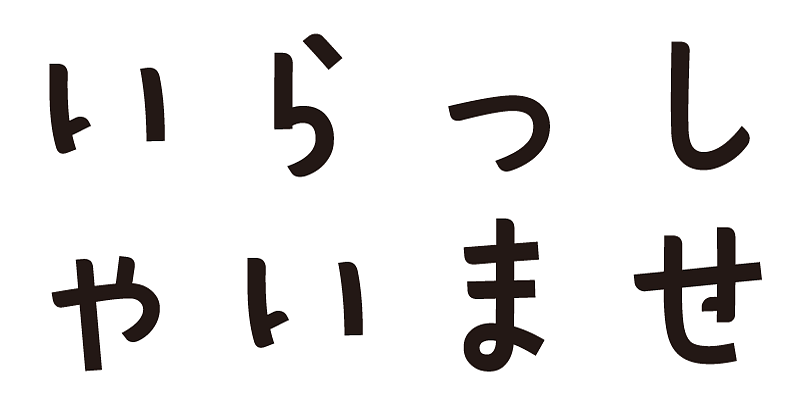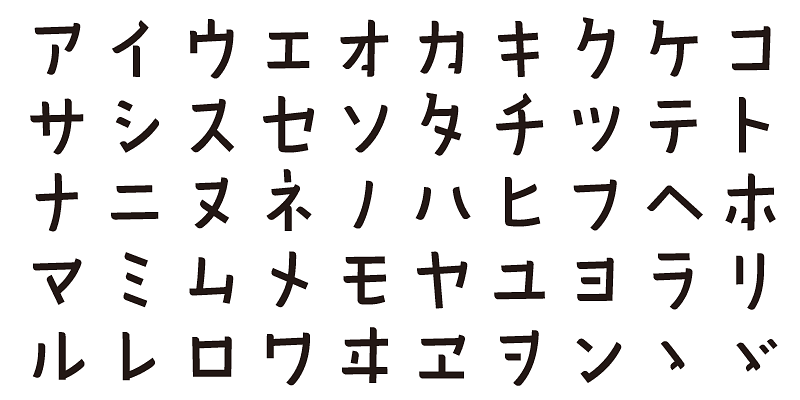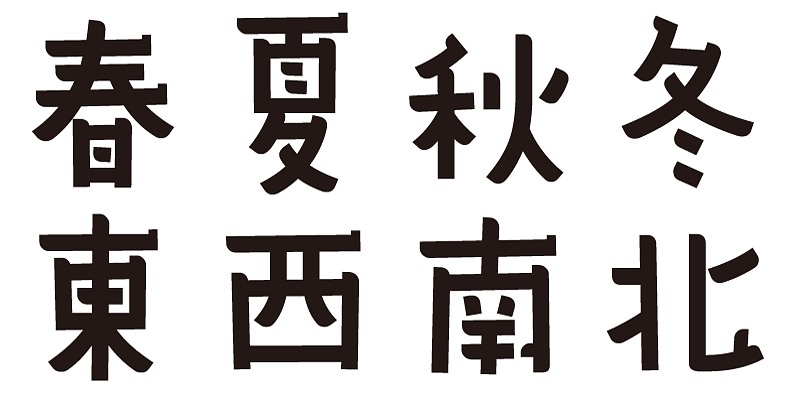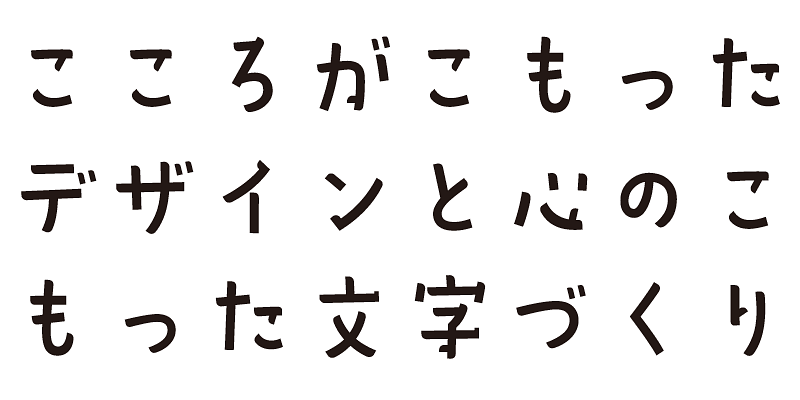
Diese Schrift wirkt sympathisch und frei, wie von Hand gezeichnet.
Jede Schrift dieser Familie enthält neben 1.000 Kanji-Zeichen auch Hiragana- und Katakana-, alphanumerische und Interpunktionszeichen.
Wir entwerfen Schriften in der Hoffnung, dass sie den ausgedrückten Worten eine tiefere Bedeutung verleihen. Wir möchten, dass sich der Benutzer bei der Verwendung dieser Schriften wohlfühlt und Freude empfindet.